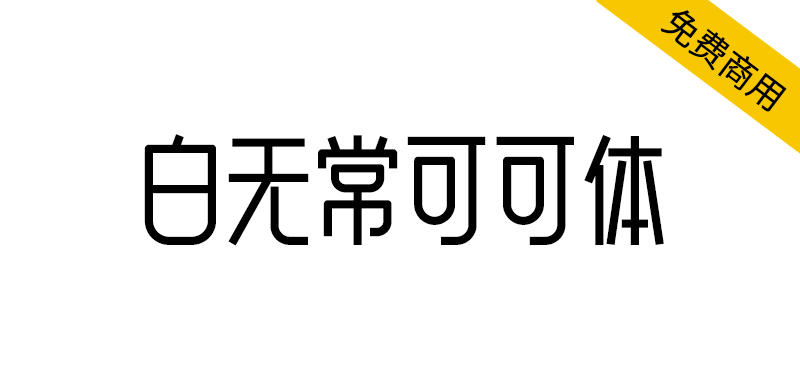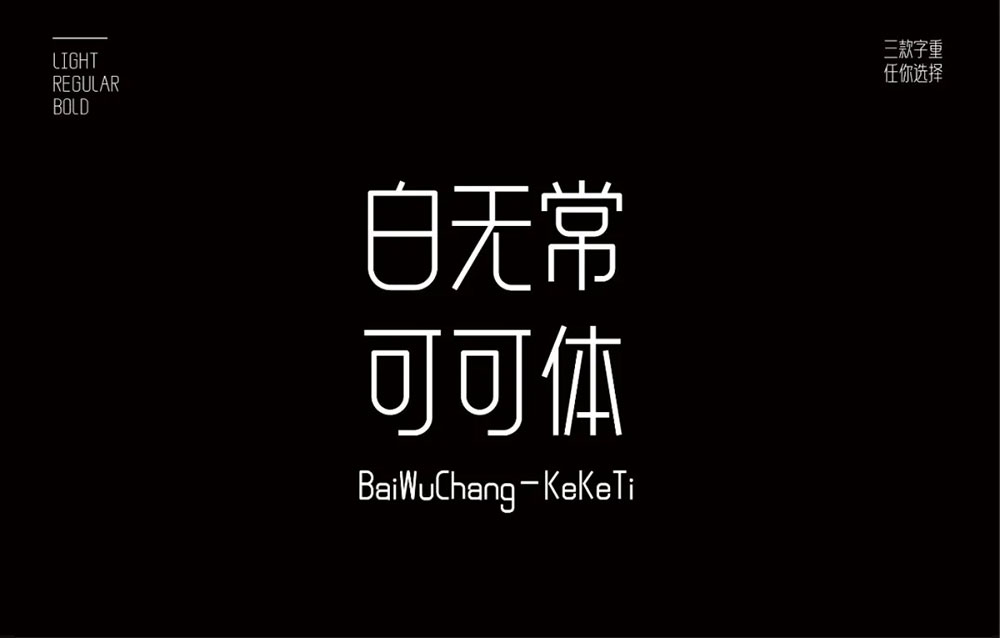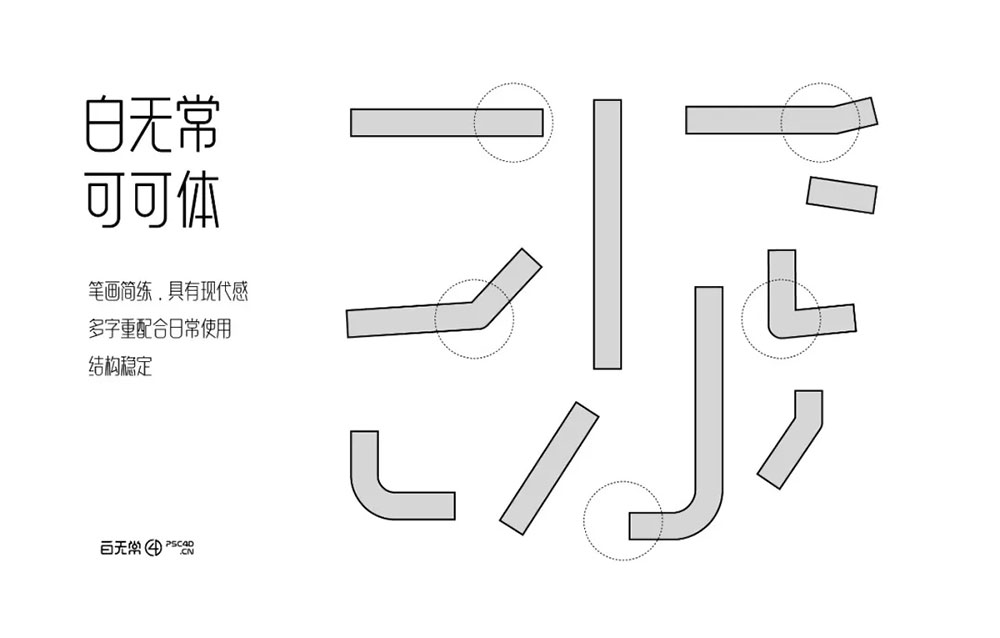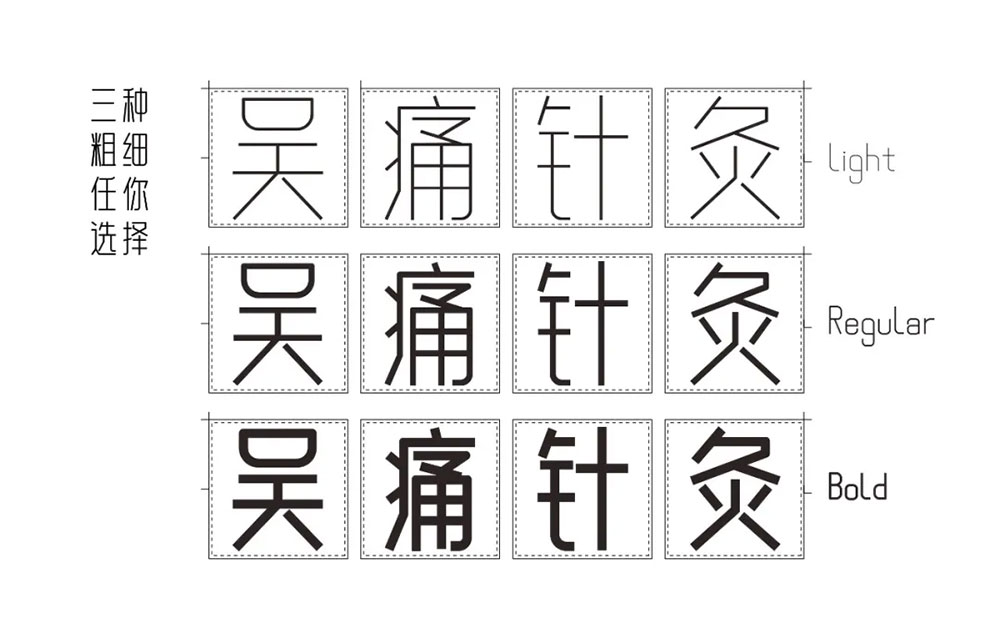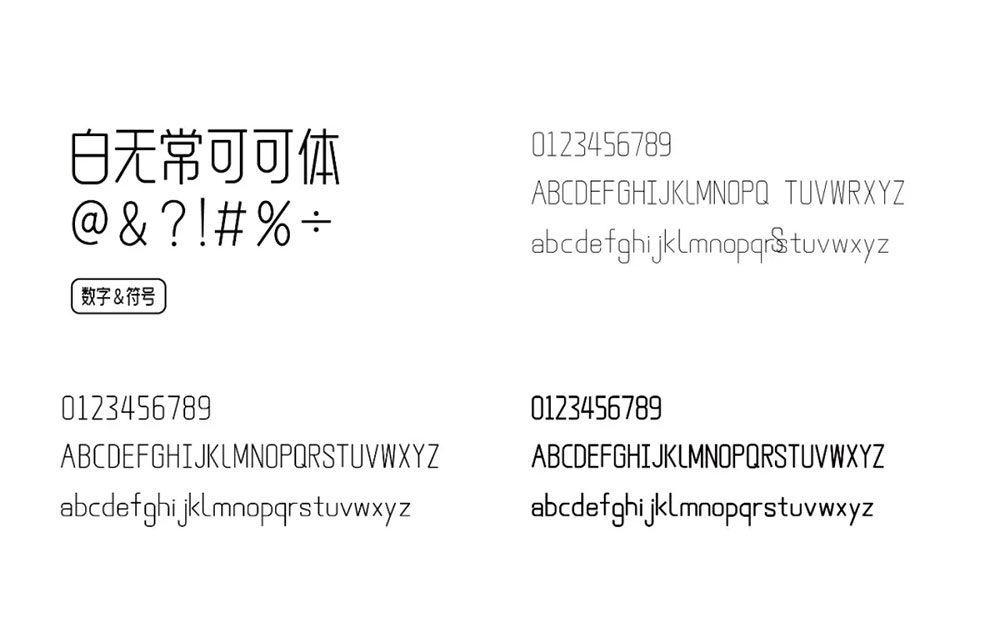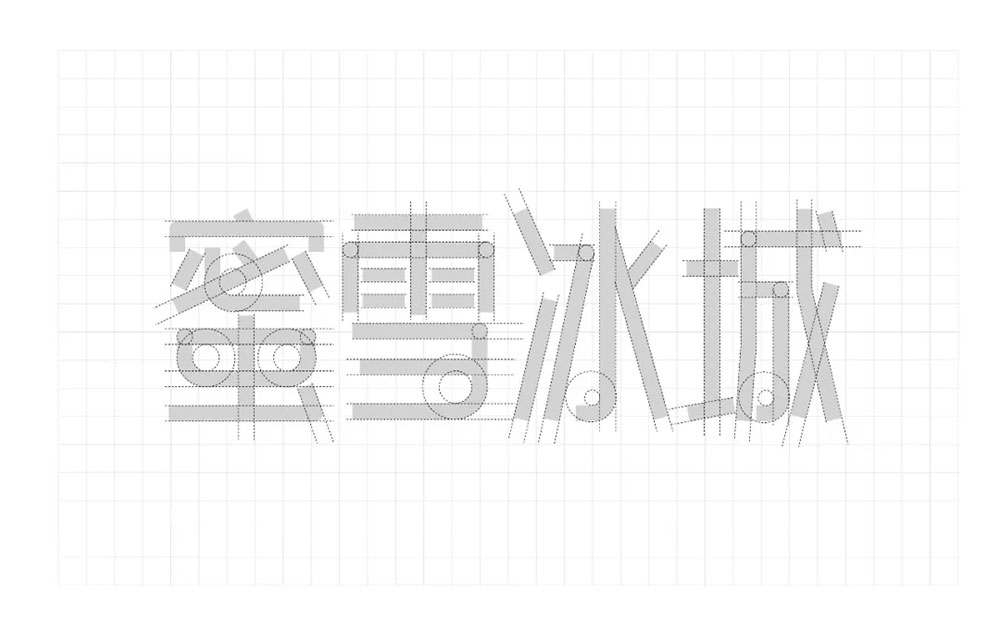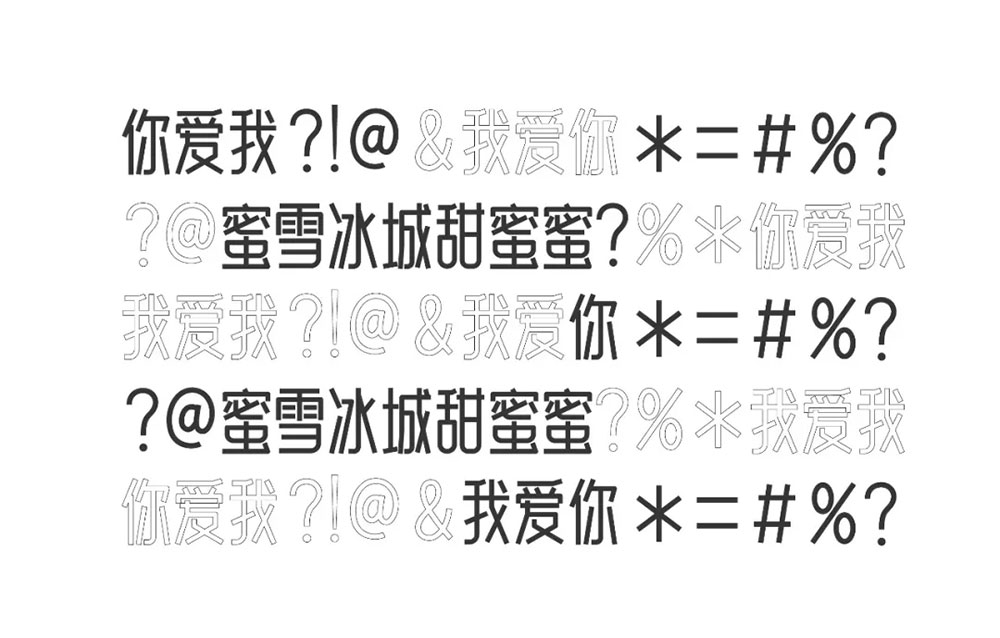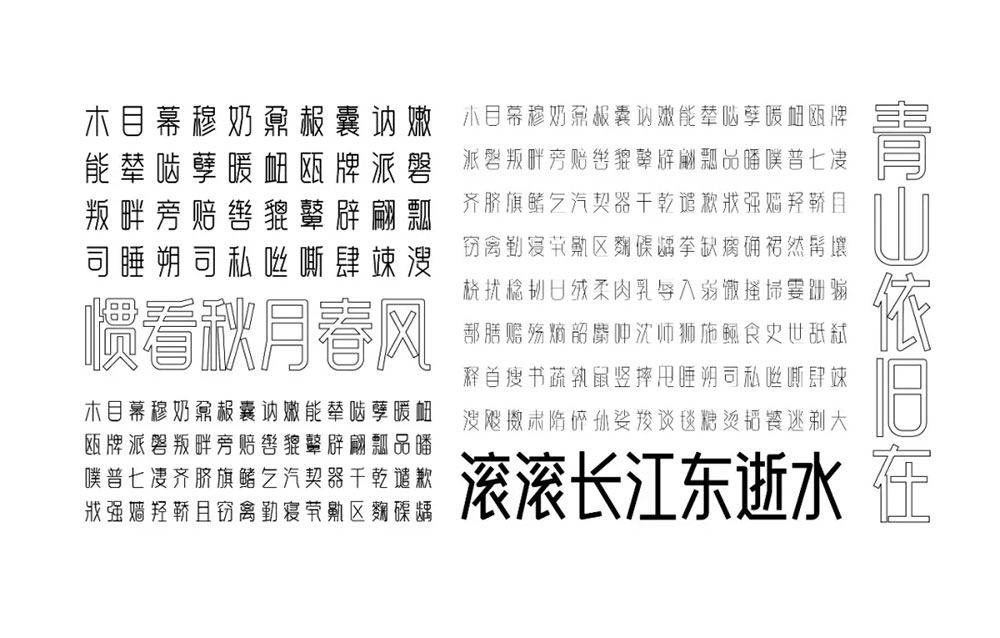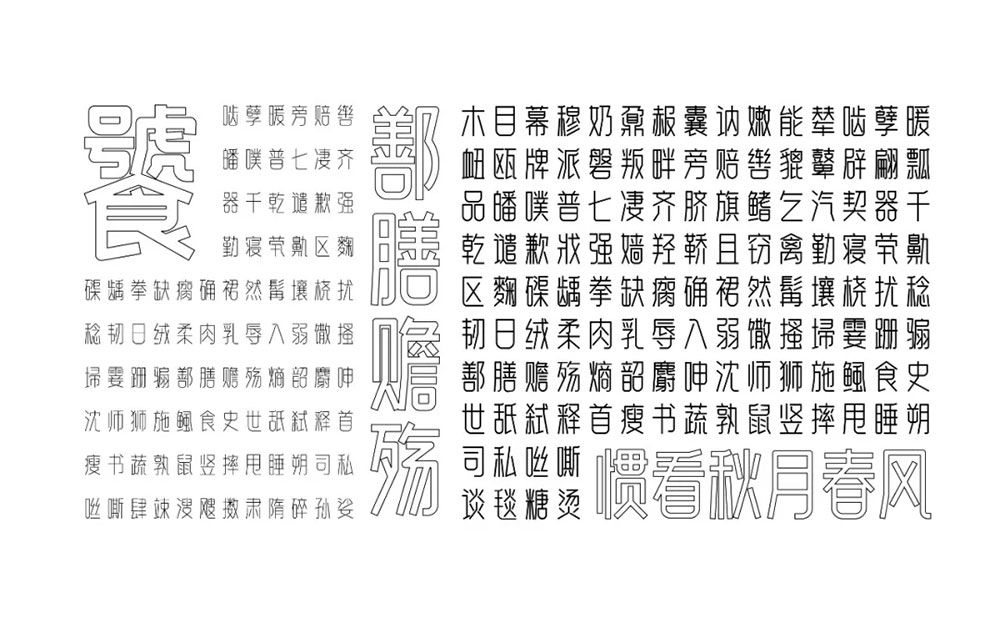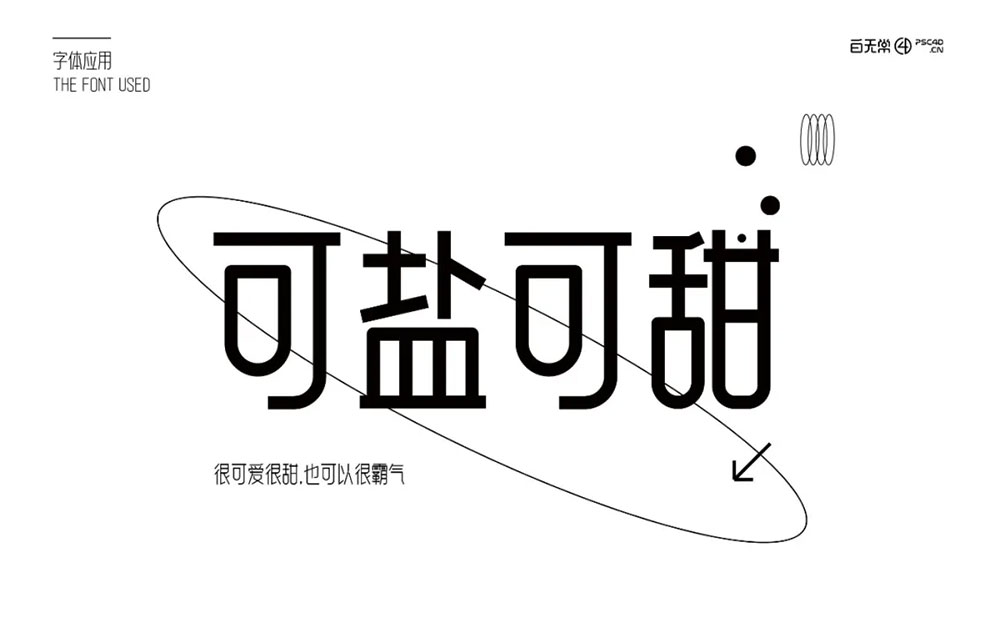
给世界留点作品:去年的时候就思考一个问题,好像每个设计作品都有它的生命周期,特别是电商这块。基本上线个几周就下线了,有些就几个小时。好像设计作品的生命的周期特别短,价值也不是特别大。就想着做字体,这个事情和发发讲了下,然后发发就离开了我们去了字节跳动,浪费人才在我这里两年既然没有让他做个字库。
白无常可可体:这款字库是我去年拜托刘兵克老师工作室制作的,一开始就想做一个好细好细的字体,连名字的想好了,白无常好细哦字体。然后兵哥告诉我,给我做了三个字重,所以不能说好细字体。非常非常感谢兵哥,给我打过折,还额外多做了二个字重!所以就换了个名字,选了一个我女儿的名字的可字,所以就叫白无常可可体,嘿嘿~~